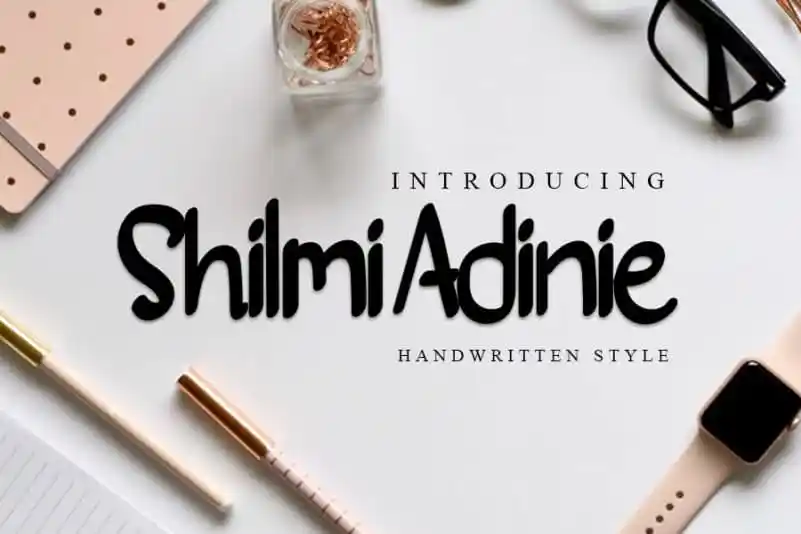
Shilmi Adinie Script Font – Download Grátis
A Shilmi Adinie Script Font é uma excelente fonte para escrita calligráfica que mantém a sofisticação das influências tradicionais dessa arte ao mesmo tempo que se atualiza e leva uma sensação de frescura moderna. Esta versatilidade é perfeita para inspirar diversas ideias criativas, desde assinaturas elegantes até designs de estação, tudo sem perder o charme e a qualidade única da fonte. Seja você um designer de logotipos, ou até mesmo alguém que aprecia uma boa impressão em papel para seus escritos pessoais, essa fonte oferece um gosto único capaz de destacar seu trabalho. Com Shilmi Adinie Script Font, todos os tipos de projetos podem ser revestidos com o toque sofisticado e criativo que a fonte promete. Ela é ideal para quem deseja dar uma pitada personalizada à sua identidade visual ou apenas quer manter um registro cuidadoso da escrita. Em suma, esta é uma fonte perfeita para aqueles que valorizam o equilíbrio entre clássico e atual, sejam eles designers gráficos ou simplesmente amantes de belas letras.